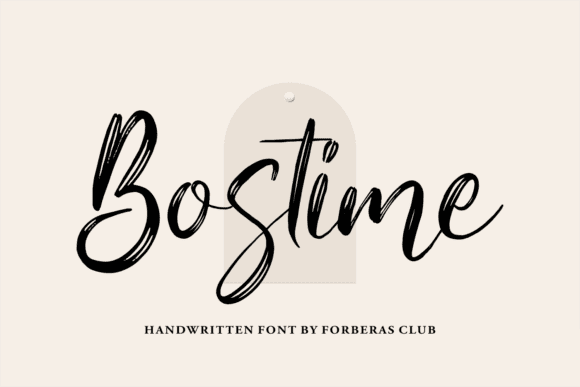
[Creativefabrica] Bostime Font (2021)
Название: Bostime Font (2021)
[Creativefabrica] Bostime Font (2021)
Bostime - это плавный, нежный и матовый рукописный шрифт.
Он характеризуется плавными изгибами и идеально подходит для модного брендинга или редакционного дизайна.